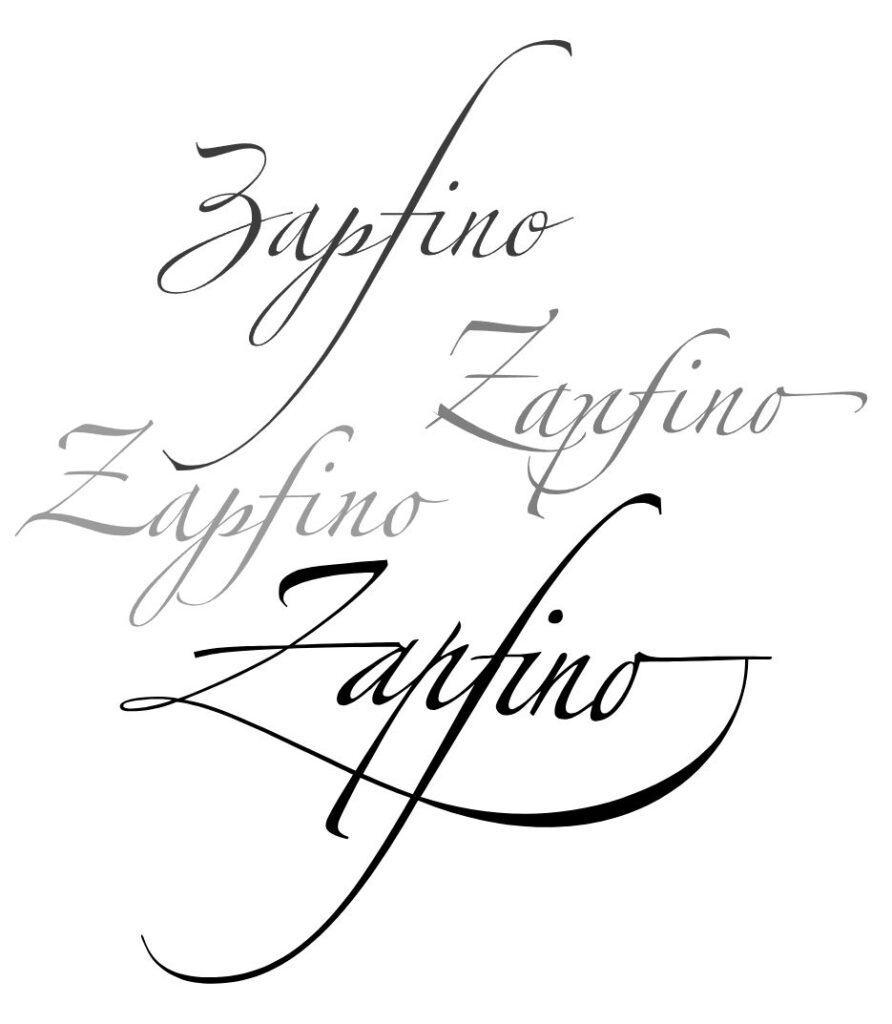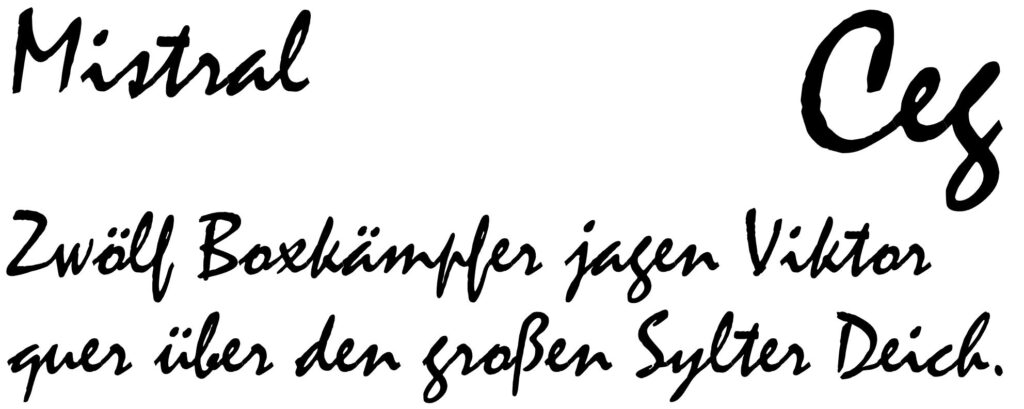
Schreibschriften
Schreibschriften orientieren sich an mit Feder oder Pinsel gezeichneten Handschriften. Sie besitzen oft ausgeprägten Wechselstrich, schwungvolle Initialen und verbindende Elemente zwischen Kleinbuchstaben. Aufgrund ihrer dekorativen Wirkung eignen sie sich weniger als Leseschrift, sondern primär für Akzidenzen und Auszeichnungen.
• Merkmale: handgezeichneter Charakter, Wechselstrich, geschwungene Anfänge, fließende Verbindungen.
• Beispiele: Zapfino (Hermann Zapf), Englische Schreibschrift, Künstlerschreibschrift, Berthold-Script, Poetic, LinoScript.